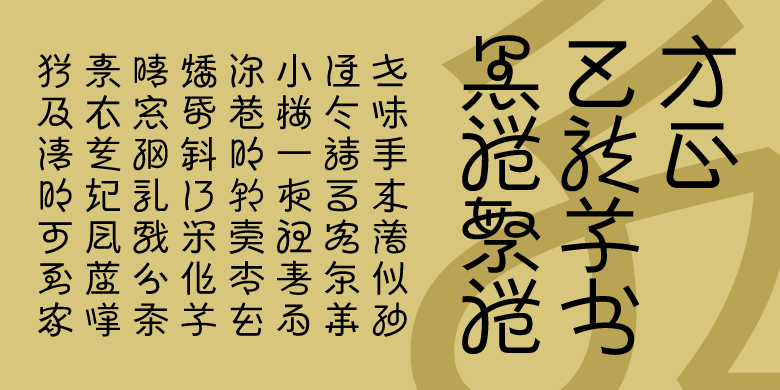
方正巴龙草书黑体
杨龙龙
创意字体
方正巴龙草书黑体是用黑体风格特点制作草书字形的一款字体,兼具草书的神秘感和黑体的时尚色彩。有带拼音和不带拼音两个版本,拓宽了它的使用范围、减小了对使用者的专业要求。字形是分析中国传统草书(今草)草法后得出的,虽然减少了传统草书书写时使转连带、保留了黑体字横平竖直的特点,但笔画关系依然明确,适合草书爱好者的学习交流以及一些有神秘感方面需求的使用者使用。